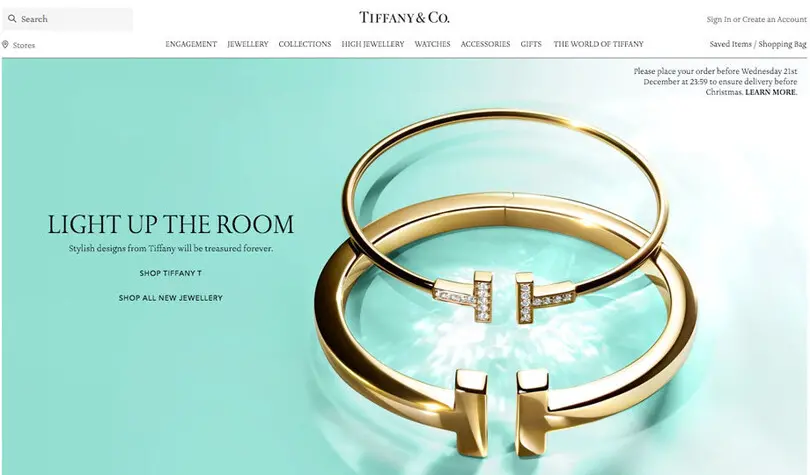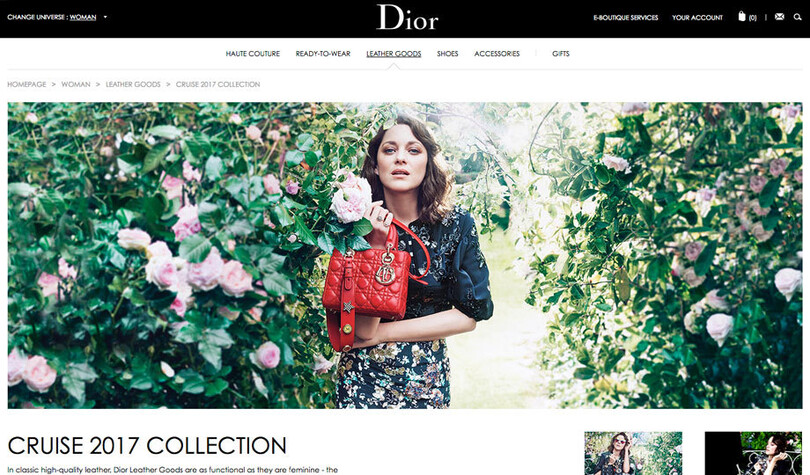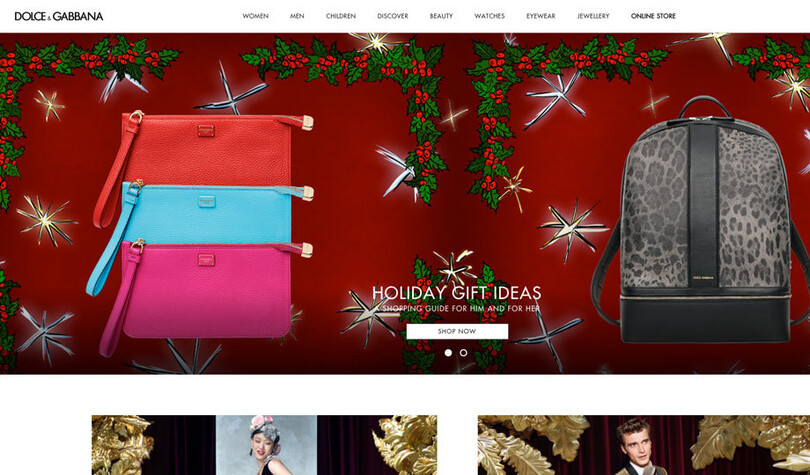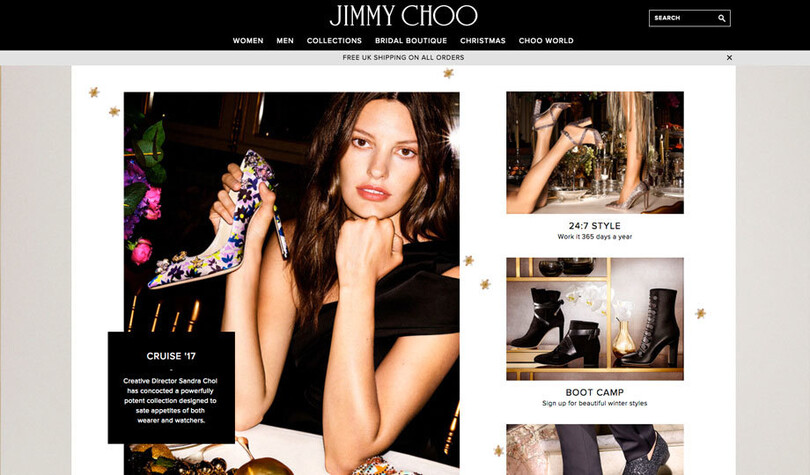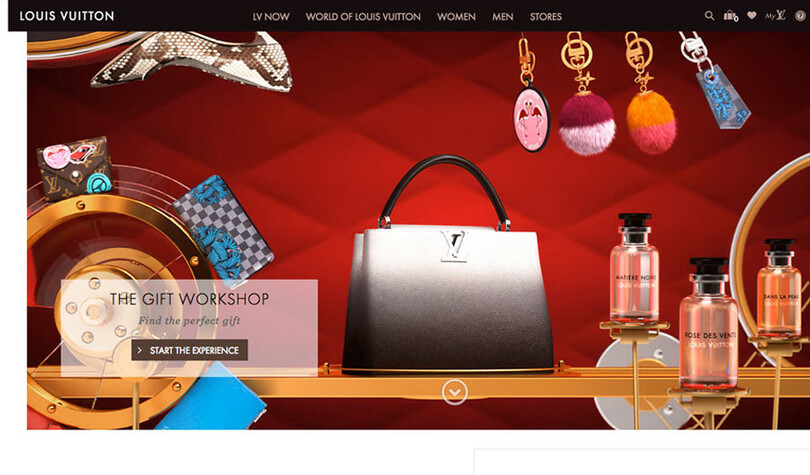
Fonts und Luxusmarken: Fashion.
Nach unserer Untersuchung der Verwendung von Fonts in der Beauty- und Automobilbranche sehen wir uns in Teil 3 zehn Luxusmodemarken an. Welches ist der modernste Fontstil? Wie nutzen diese Marken Schriftarten, um sich von ihren Mitbewerbern abzuheben, und gibt es verpasste Chancen?
Gucci
Große Bilder und geometrische Typografie schaffen ein Gefühl von Eleganz, Modernität und Luxus. Die Verwendung von Futura im Fließtext ergänzt perfekt Granjon im Logo. Beide sind breit, offen, zugänglich und unaufdringlich. Die Verwendung von Times in den Artikelbeschreibungen verstärkt das Gefühl von Luxus, ist aber eine kostenlose und unoriginelle Wahl mit haarfeinen Strichen, die sich bei den verwendeten kleinen Größen nicht gut behaupten.
Tiffany & Co
Eine kontrastreiche, zarte Serifenschrift namens Sterling von Hoefler Type Foundry wird sowohl im Logo sowohl auch als primärer Font verwendet. Durch die hauchdünnen Haarstriche verschwindet die Schrift in kleinen Größen, insbesondere im Navigationsmenü. Das Menü und die Bildtexte werden ganz in Großbuchstaben gesetzt, und der Fließtext in Groß- und Kleinschreibung. Dies sieht luxuriös und elegant aus. In einigen Bereichen werden auch humanistische Sans Avenir Next (und Helvetica) verwendet, um einen modernen Akzent zu setzen.
Jimmy Choo
Der Kontrast zwischen der schmalen und der breiten Form der Exklusiven University Roman JIMMY CHOO Wortmarke ermöglicht es der Hauptschrift Proxima Nova, sich zu entfalten und eine dynamische visuelle Beziehung herzustellen. Die schlichte Fotografie in Verbindung mit der sauberen, modernen und lesbaren Proxima Nova schafft ein elegantes, klassisches und dezent schlichtes Flair.
Louis Vuitton
Das exklusive „LV“-Monogramm hat dicke, klobige Serifen und gewichtete dünne Striche. Es basiert auf der Schriftart Georgia und wirkt stark und robust. Futura wird für die Wortmarke „Louis Vuitton“ und den Text verwendet, sodass ein schönes visuelles Gleichgewicht zwischen den beiden Schriften entsteht, die sich voneinander gut absetzen. Auf ihrer Website wird Georgia auch für Text eingesetzt, wobei Austin Roman und LV Clemence sporadisch verwendet werden, um eine leicht verwirrende typografische Hierarchie zu schaffen.
Dior
Die Dior-Wortmarke verkörpert Eleganz, zusammen mit den reichen und dynamischen Bildern in Bildschirmgröße, die gut mit den Fonts harmonieren und ein Gefühl von Stil, Klasse und Kultiviertheit vermitteln. Die unterstützende Schriftart ist Century Gothic, wobei die Bildtexte ganz in Großbuchstaben und der Fließtext in Groß- und Kleinbuchstaben gesetzt sind. Die Verwendung von Century Gothic Light lässt den Text grau erscheinen, wodurch er fast im Hintergrund verschwindet. Die Website verwendet auch den Systemfont Arial.
Prada
Das Prada-Logo ist eine moderne Serifenschrift, die kühn, legendär und unverwechselbar ist. Die Marke verwendet auf ihrer Website große, bewegte Bilder, die sich mit minimaler Typografie über das gesamte Layout erstrecken. Das Hauptnavigations-Menü ist in Univers in Großbuchstaben gehalten, während der Fließtext in einem kostenlosen Open-Source-Font namens Source Sans Pro gesetzt ist. Prada hat die Gelegenheit verpasst, den eigenen Stil in der Typografie widerzuspiegeln, die wie ein nachträglicher Entwurf wirkt.
Burberry
Das Burberry-Logo ist eine exklusive erweiterte Version von Bodoni, einer modernen Serifenschrift, die hohe Qualität und Luxus vermittelt. Proxima Nova ist der primäre Font für Überschriften, Bildtextsatz und Fließtext in Groß- und Kleinbuchstaben. Viele dieser Schriften (Navigation und Text) sind klein und schwer zu lesen. Die sekundäre Schriftart (Times) ist eine weitere einfallslose Wahl, die kostenlos verwendet werden kann.
Armani
Der haarfeine Charakter des Armani Didot Logos tritt zuweilen in den Hintergrund, aber diese Schrift ist ein klassisches Beispiel für Luxus, Stil und Couture. Montserrat ist ein robuster, offener und harmonisch geometrischer Sans. Dunkle, maskuline Farben erstrecken sich über die Landschaft und die seriöse Bildsprache.  Die Marke ist modern, klassisch und legendär – und die Typografie spiegelt dies wider.
Manolo Blahnik
Manolo Blahnik hat sich für Arial entschieden und es ist der einzige verwendete Font. Es sieht sehr einheitlich aus, aber Arial ist ein Neo-Grotesque, der auf jedem x-beliebigen Computer zu finden ist. Daher ist es eine merkwürdige und einfallslose Wahl für eine solche High-End-Marke. Positiv zu vermerken ist, dass viele Arbeitsstunden für das Hinting dieses Fonts für die Verwendung am Bildschirm aufgewendet wurden, sodass er sehr funktionell ist. Er wurde auf einem weißen Hintergrund mit viel Raum gesetzt, um ein Gefühl von Kultiviertheit zu erzeugen. Für Überschriften und Navigation wurden neben sehr luxuriöser Bildsprache Großbuchstaben verwendet, aber der Einsatz von Kernfonts ist in diesem Sektor im Hinblick auf die Markendifferenzierung eine verpasste Gelegenheit.
Dolce & Gabbana
Bei dieser Marke handelt es sich um eine Sammelsurium verschiedener Fonts, die in unterschiedlichen Stilen verwendet werden. Neben dem geometrischen Sans, dem Übergangsserifen und dem humanistischen Sans gibt es eine kreidige Handschrift und ein Bodoni! Eine wilde Mischung aus Stil und Persönlichkeit. Das D&G-Logo ist in Futura Bold gehalten und hat breite, runde und geometrische Proportionen. Die leichteren Schriftstärken, die in der Navigation und in Bildtexten verwendet werden, vermitteln ein Gefühl von Anmut und Eleganz, aber mit der fehlenden Kohäsion zwischen Futura und Avenir tut sich diese Marke keinen Gefallen.
Insgesamt besteht die Tendenz, dem Stil Vorrang vor der Funktion einzuräumen, und es besteht ein überraschender Mangel an Fantasie, wenn es um die Typografie geht. Beim Schriftsatz gibt es grundlegende Probleme in Bezug auf Gewicht, Farbe und Größe. Viele der Layouts sind auf dem Bildschirm einfach nicht lesbar (z. B. Burberry, Tiffany, Dior und Gucci). Die Verwendung kostenloser Fonts ist üblich und steht im Widerspruch zum Luxusimage. Die Marke ist alles, und obwohl nicht jede Marke den Wert einer Exklusivschrift erkennen wird, gibt es durch die Verwendung von Arial oder Times keinen Unterschied zwischen High End und Budget, insbesondere auf mobilen Geräten, wo nur wenig Platz für Bilder vorhanden ist.